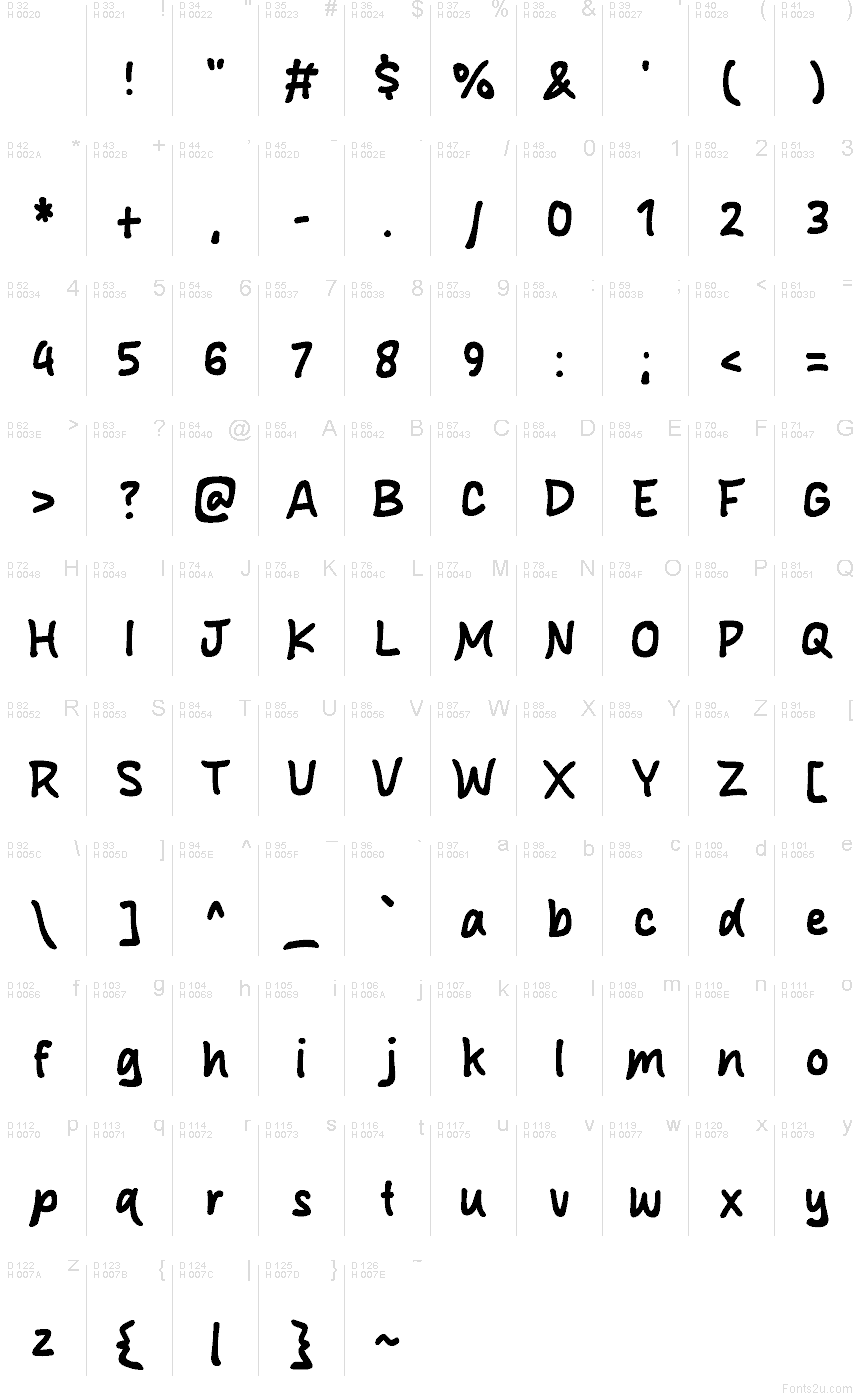
Strange Neighbor
Strange Neighbor od MJType je bezplatné ručne písané písmo v štýle fixy s výrazným, uvoľneným rytmom. Písmená pôsobia, akoby boli nakreslené rýchlo, s mäkkými zaoblenými krivkami, hrubými ťahmi a ľahko hravým tokom, vďaka čomu si písmo udržuje ležérny, nie príliš uhladený vzhľad.
Hodí sa pre plagáty, branding kaviarní, obaly, grafiku na sociálne siete i neformálne nadpisy, kde chcete niečo ľudské a výrazné, bez toho, aby to pôsobilo strnulo. Ako bezplatné písmo sa skvele hodí aj pre titulky, krátke nadpisy a citáty, pretože široké ručne písané tvary dodávajú aj krátkym slovám na živosti a osobnom charaktere.